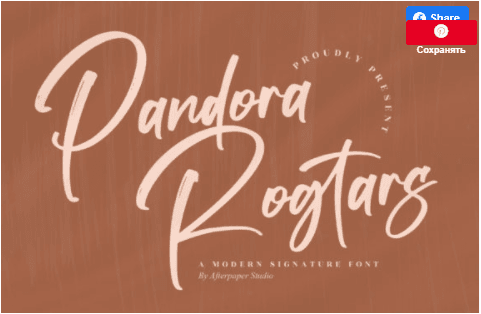
Pandora Rogtars Font
Pandora Rogtars — красивый рукописный шрифт. Он подходит для любых проектов, таких как: логотипы, проекты брендинга, пригласительные билеты, поздравительные открытки, этикетки, фотографии, водяные знаки, специальные мероприятия и все другие ваши прекрасные проекты, которым нужна стильная атмосфера. Этот шрифт имеет кодировку PUA, что означает, что вы можете легко получить доступ ко всем глифам и росчеркам!